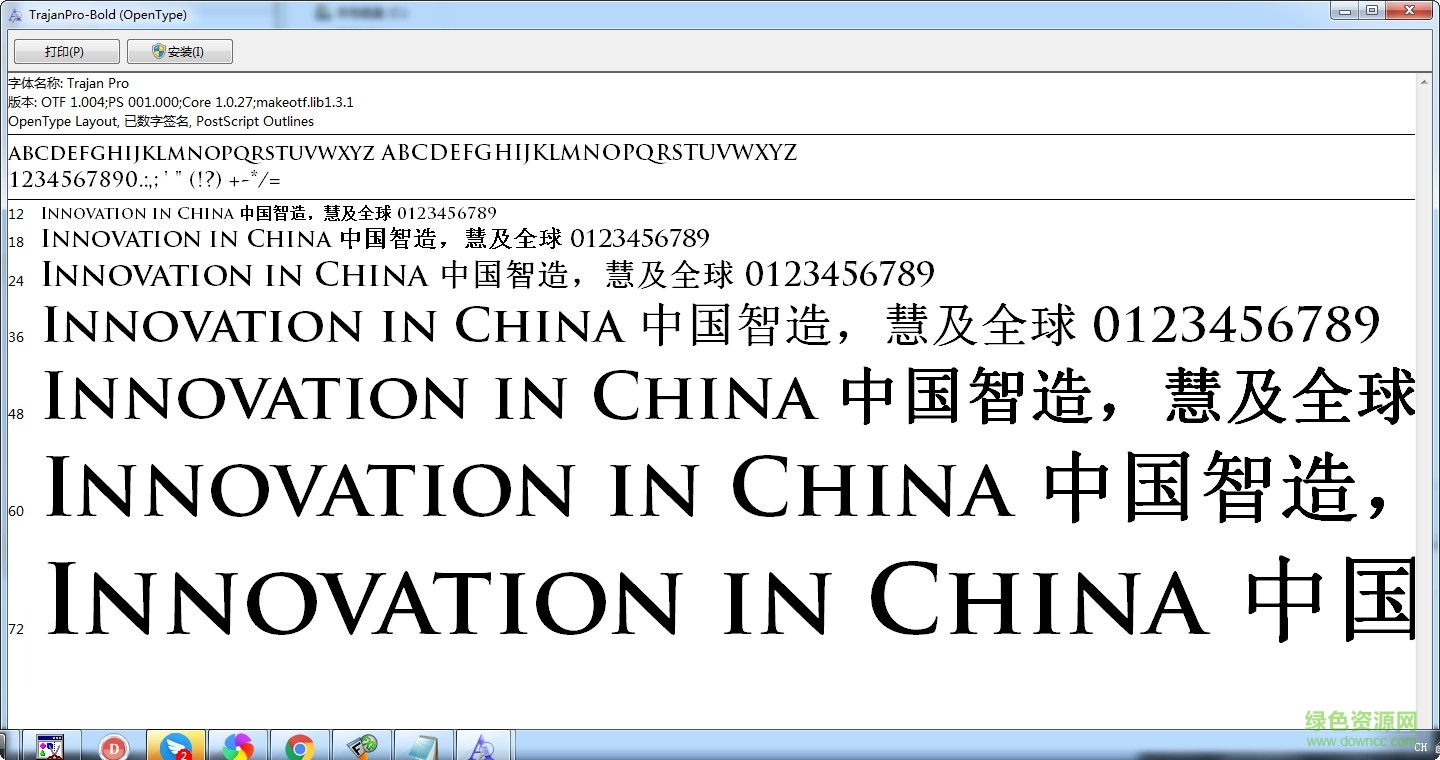
Trajan 是一種襯線字體,是卡羅·吐溫布里(Carol Twombly)在1989年為Adobe公司設計制作的。 Trajan一詞本身,是羅馬帝國皇帝圖拉真名字的英文拼寫。該字體的設計基于“古羅馬方塊大寫字母”(capitalis monumentalis)的風格,常用于公元一世紀古羅馬石柱石碑雕刻使用。由于羅馬時代還沒有使用小寫字母,因此Trajan字體全部都是大寫字母。代替小寫字母的,是一種小型大寫字母。這種古風字體廣泛用于古羅馬石碑上。近來一些電影海報、電視和書籍封面也經(jīng)常使用這種字體。